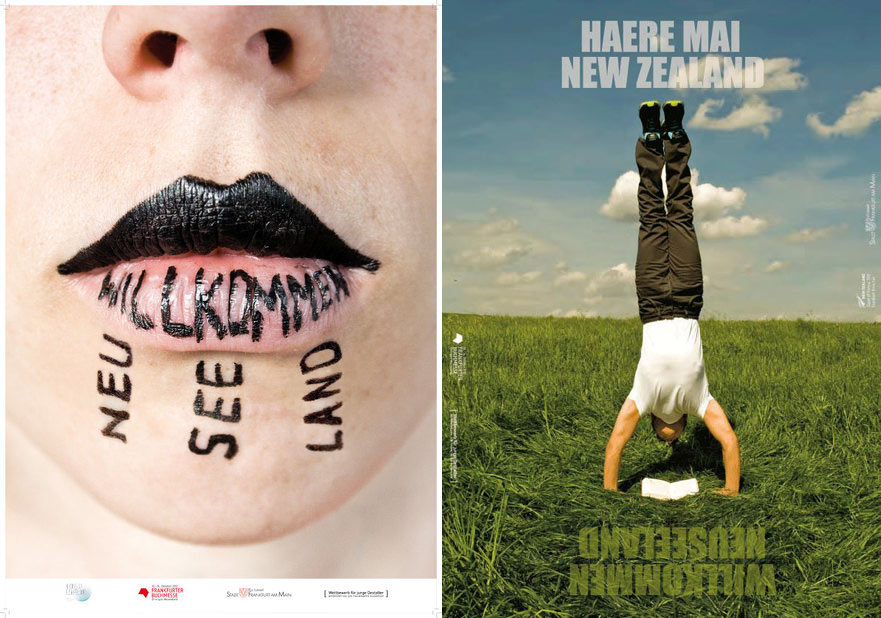
Unsere Abbildung zeigt die beiden Plakate, die ab September in Frankfurt hängen und das Partnerland der diesjährigen Buchmesse willkommen heißen werden. Es sind die beiden besten von insgesamt 80 Entwürfen, mit denen junge Gestalter – Studierende von vier Hochschulen aus dem Rhein-Main-Gebiet – am Wettbewerb der Frankfurter Buchmesse teilgenommen haben. Weitere Siegermotive sind bis zum 1. Juli 2012 in der Ausstellung des Museums für angewandte Kunst in Frankfurt zu sehen.
Das Siegermotiv von Denis Schmitt (Hochschule RheinMain, Wiesbaden) variiert ein traditionelles Maori-Tattoo: statt ornamentaler Linien findet sich schwarz aufgepinselter Text auf Lippen und Kinn. Der tätowierte Mund betone die Erzähltradition Neuseelands, lobte die Jury in ihrer Begründung. Das Gesicht wirke »offen und ehrlich, gleichzeitig punkig und subversiv – Eigenschaften, die man sowohl Neuseeland als auch Frankfurt zuordnen kann.«
Das zweite Motiv entwarf Anne Battenfeld (Hochschule Darmstadt), die auf ihrem Plakat einen Mann im Handstand lesen lässt. »Ein klassisches Zitat des Ehrengastes Neuseeland, der von Down-under, vom anderen Ende der Welt kommt«, befand die Jury.
Das zweite Motiv hätte ich mir gut auf dem Kopf vorstellen können. Ich glaub’, so war das auch geplant. Komisch.
Zum Glück gibt es Erklärungsversuche. Diese Aussage zu Motiv 1 hätte sich mir nicht erschlossen. Hatte es schon die die Kategorie “Was soll das?”, schlechter Sagmeister-Abklatsch?, gepackt. Ich finde die Umsetzung nicht sonderlich gut gelungen.
ich hätte das ausgewählt:
überraschender, lustiger, schöner.
Motiv 1 ist sehr schlecht lesbar und irgendwie dilletantisch umgesetzt ohne den Charme von Handgezeichnetem… Ausserdem ist die Analogie zu den Maori-Tätowierungen sehr schwer zu erkennen….
So als einfache Buchmessenbesucherin fand ich ehrlich gesagt von allen Vorschlägen den insbesondere den folgenden einfach klasse:
Ohja. Das macht fast die gleiche Aussage, funktioniert aber viel besser .
Stimmt. Maori-Tattoos zeichnen sich durch die Vewendung von Linien aus.
… mir hat ein neuseeländischer freund erzählt, dass es als Beleidigung gilt, wenn Menschen die nicht dort geboren sind und sich nicht “diesen Status verdient” haben, ein Maori-Tattoo tragen. By the way sind beide Plakate unfassbar Klischee behaftet, wenig plakativ und schlecht umgesetzt. Da gab es bessere. Aber ansich sollte man den ganzen Wettbewerb mal in Frage stellen. Warum gibt es denn bitteschön zwei Plakate (ein offizielles und eben das aus diesem Wettbewerb) die beide gleichzeitig in der Stadt aushängen? Gerade uns Kommunikationsdesignern wird doch immer gelehrt, dass die reine Form an sich nicht entscheidend ist sondern das Konzept stimmen muss. Für mich stimmt das Konzept hierbei nicht.